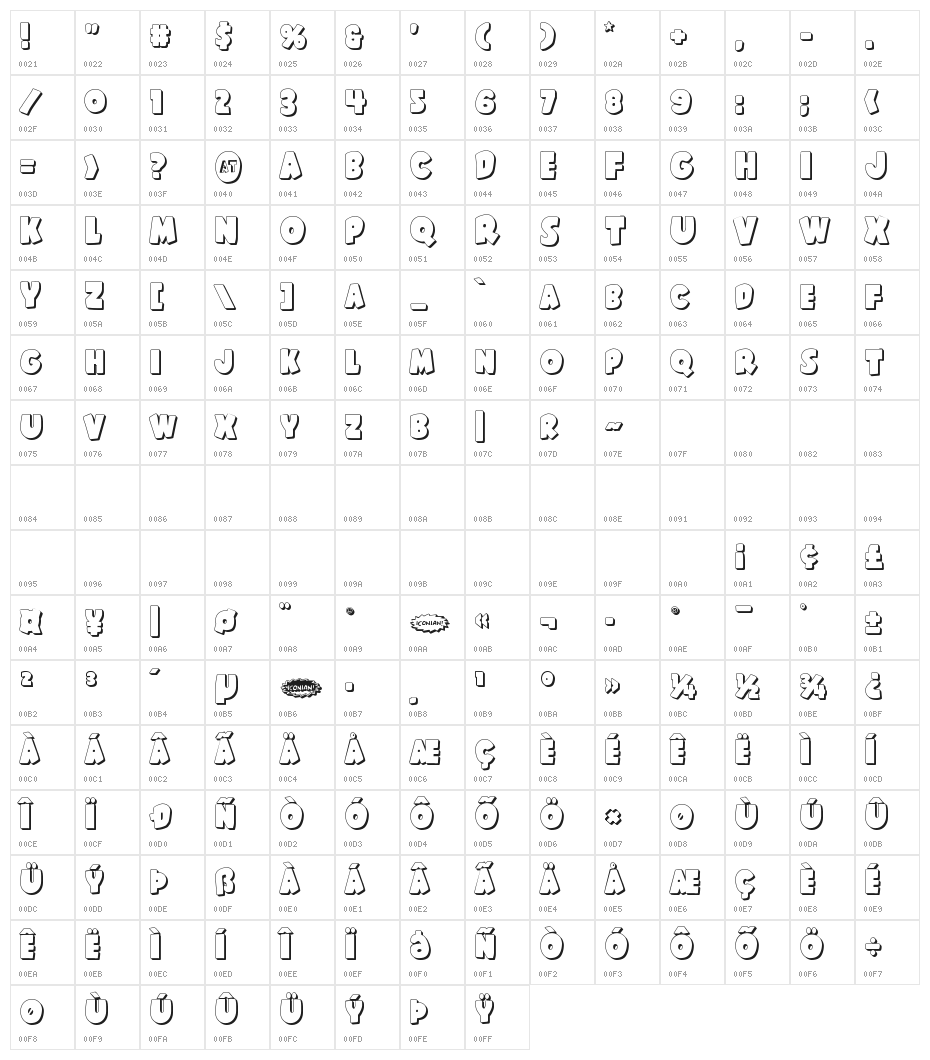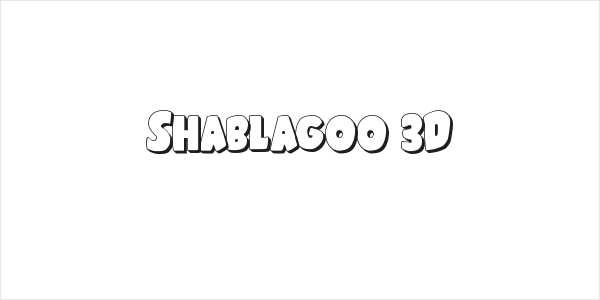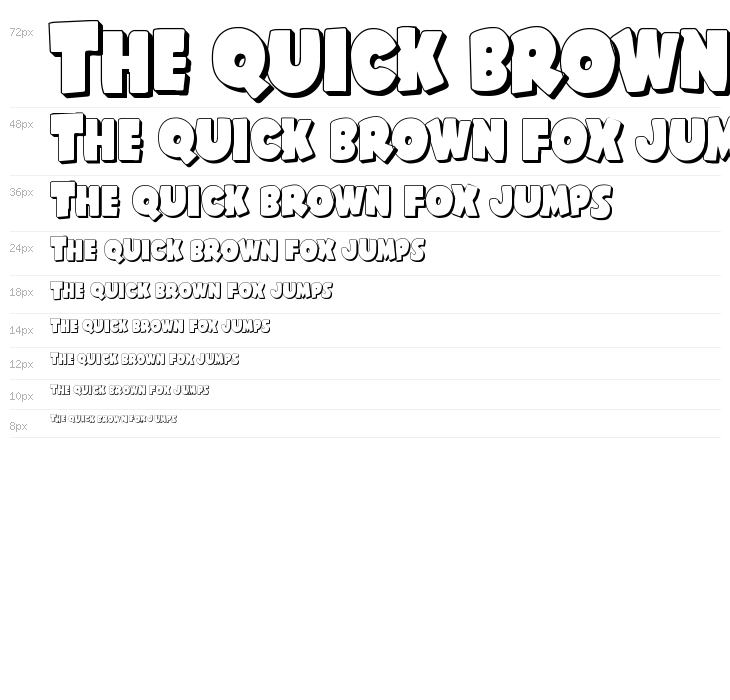
Shablagoo 3D Font
✎ Cartoon
| Estilo general | Playful, Cartoonish, Fun |
| Caso de uso | Headlines, Posters, Branding |
| Proyectos propuestos | Ideal for children's books, comic strips, playful branding, and eye-catching posters. |